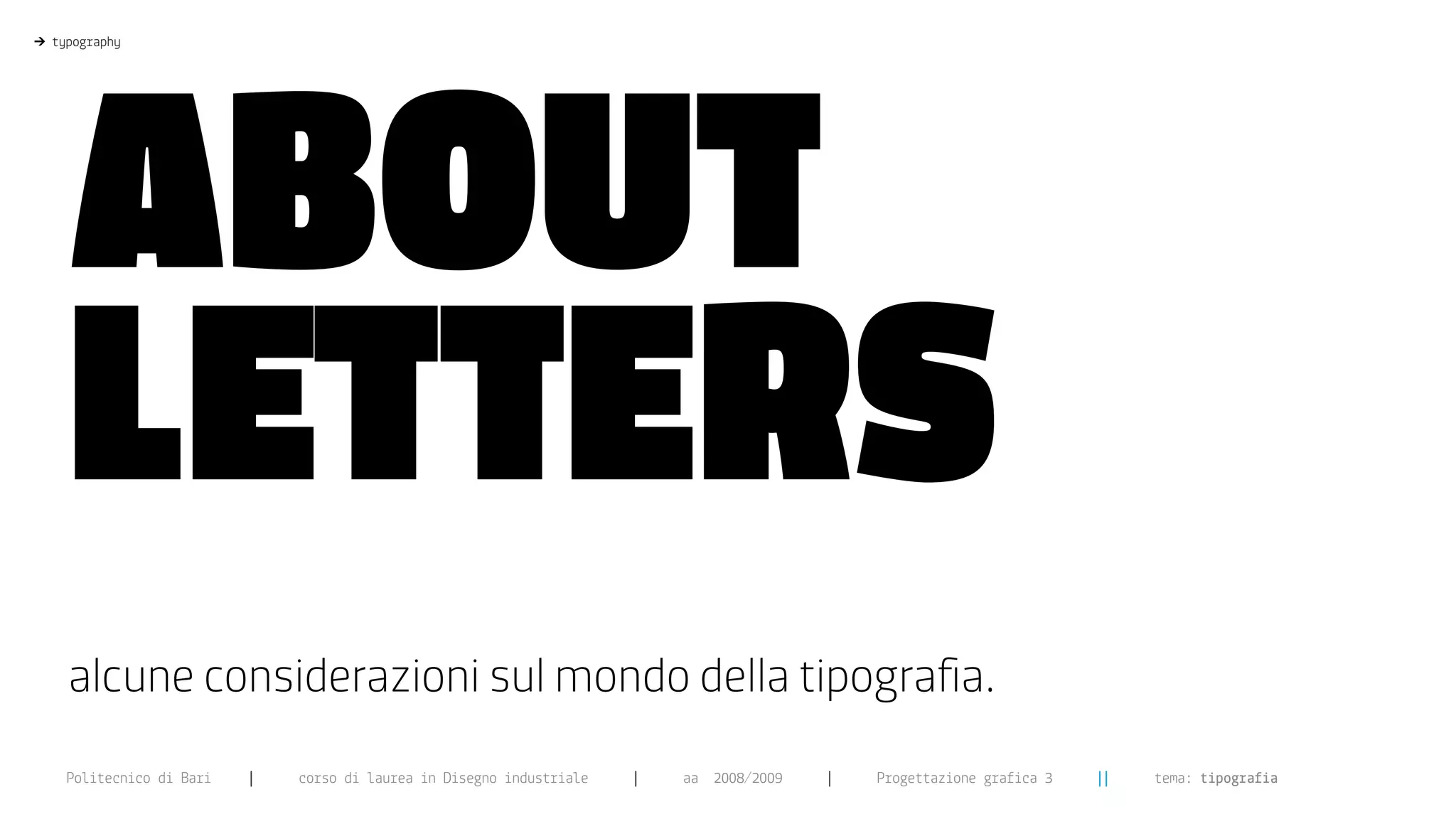
ABOUT
>   typography
LETTERS
alcune considerazioni sul mondo della tipografia.
COSA è UNA
LETTERA?
>  UN SegNo grafico con cui                                                  >  Per lettera s’intende ogni SegNo
per convenzione si rappresentano                                             del SiStema coNveNzioNale, detto
i SUoNi in un alfabeto                                                       alfabeto, che permette di fiSSare
UN diScorSo in maniera visibile
>   UN SegNo alfabetico con cui
su di un supporto.
si indicano un ente, una funzione
matematica o numeri indeterminati                                            > In linguistica, si dice che
UN foNema vieNe rappreSeNtato
> UN carattere tipografico
da UN grafema.
per la stampa
> In tipografia si parla di carattere
d’UN determiNato foNt.
> tUtto è iNiziato                                                           >  le lettere svolgevano una
coN aleph, e l’alfabeto                                                      funzione rappresentativa
proto-SiNaitico.                                                             di concetti, immagini, azioni,
che oggi non svolgono più.
> eSiSte UNa pSicogeNeSi                                                     ogni glifo possiede una memoria.
dell’alfabeto.
>    esse sono in effetti
>  la ScrittUra è Nata                                                       “immAgini dEcAdUTE” .
come SiStema aperto.
l’alfabeto come SiStema
chiUSo è veNUto dopo.
di cOSA
>   typography
SOnO FATTE
LE LETTERE?
>   ROLAND BARTHES
> SpiritoSo... queSta è una bella domanda, infatti non è tua! ma è una domanda
che Si è poSto roland barteS, ed è belliSima perché non ha riSpoSta, e perciò
da modo di ricercare Senza fine... le lettere generalmente Sono conSiderate
come Segni bidimenSionali, in verità Sono dei veri e propri oggetti, oggetti di
deSign, come ha Scritto eric gill, le lettere Sono coSe, e perciò come tutti gli
oggetti hanno un progettiSta, un motivo per cui vengono progettate, hanno tre
dimenSioni, e certe volte anche quattro o più dimenSioni perchè variano da pochi
micron di inchioStro fino a grandiSSimi volumi. (famoSe alcune architetture
faSciSte aventi la m di muSSolini come pianta). poSSono avere anche la dimenSione
del tempo, penSiamo a titoli di teSta notevoli di film, e ve ne Sono innumerervoli,
ma Soprattutto hanno la dimenSione altra, che è quella del penSiero.
IL DISEgNO DI uNA LETTERA DEvE RAppRESENTARE SOpRATuTTO uN pENSIERO.
Sonnoli
LE LETTERE
>   typography
SOnO FATTE
di VOLOnTà
>   ZAELIA BISHOp
>       RAPPORTO
TRA IL SEGNO
E IL SUONO